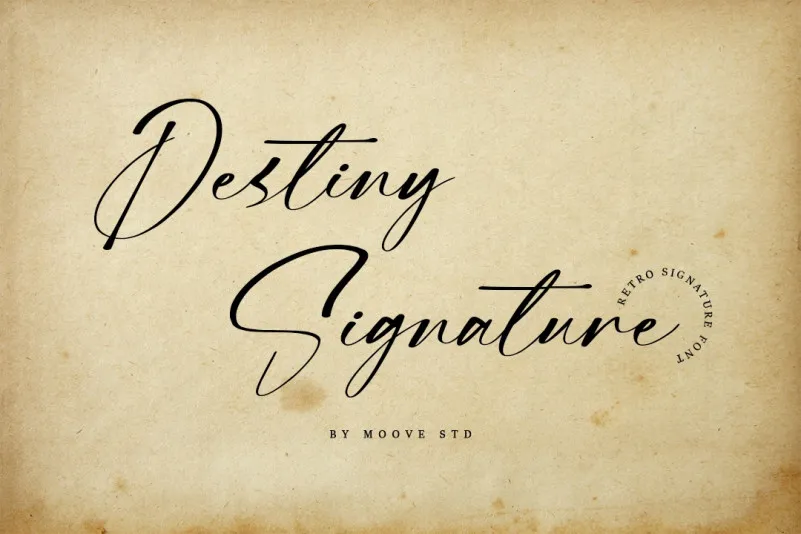
Esta é uma fonte script elegante e com um toque romântico perfeito para aquelas projetos que precisam de uma aparência fresca e sofisticada. Ela foi criada pelo designer talentoso do Moove Studio, disponível no site 99designs. Com sua delicadeza e estilo refinado, esta fonte é ideal para designers buscando adicionar um toque único a seus projetos. Seja em cartazes, logotipos ou design de escrita, ela traz elegância ao seu trabalho sem tirar o interesse do seu público-alvo. Esta elegante fonte é perfeita para aqueles que buscam uma alternativa moderna à script clássico, oferecendo um tom romântico e sofisticado. Em um mundo onde muitas vezes buscamos combinar elementos antigos com design contemporâneo, a Destiny Signature Font se destaca como o elemento perfeito para tornar seu projeto único.